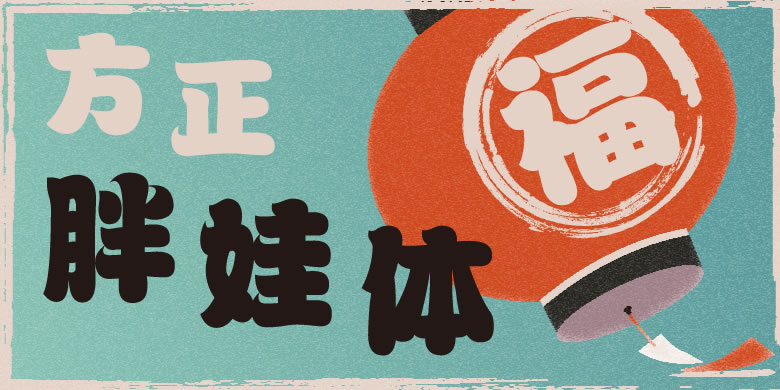
字体介绍 品牌:方正字库设计师:齐立发行时间:2000字库编码:大陆简体(GB2312-80)、大陆繁体(GB12345-90)、简繁扩展(GBK)、港台地区(BIG-5)分类:创意字体 英文名称:FZPWJW.TTF 方正胖娃是一款用曲线来模拟短锋毛笔书写特征的创意字体。这款字体非常注重曲线的刻画,线条柔美,笔画粗细富有变化,起笔和收笔婉曲而利落,字形丰腴。方正胖娃的个性天真敦厚,亲切可爱,适用于杂志和书籍的封面,以及品牌广告和产品包装设计。 字体下载 官方下载